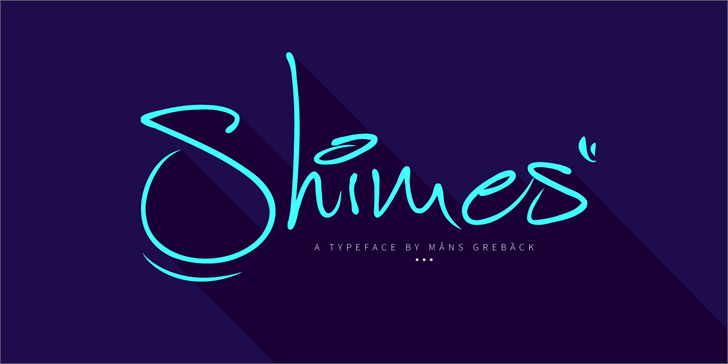
Shimes font
A Shimes é uma fonte script que oferece um toque suave e elegante para textos digitais. Seu designer Hamilton criou a Shimes para fornecer um estilo único e fluido, perfeito para adicionar um toque sofisticado a qualquer projeto de design. Com sua simetria perfeita e linhas leves, essa fonte é ideal para uso em nomes comerciais, logotipos ou até mesmo textos gráficos. A Shimes não apenas oferece uma experiência visual interessante, mas também se adapta facilmente a diferentes tamanhos de texto, permitindo um desempenho consistente e profissional em qualquer situação. Se você está procurando por uma fonte script que possa destacar seu design, Shimes é uma escolha segura para sua biblioteca de recursos gráficos. Visite o site da MansGreback para mais informações sobre aquisição de licenças comerciais.